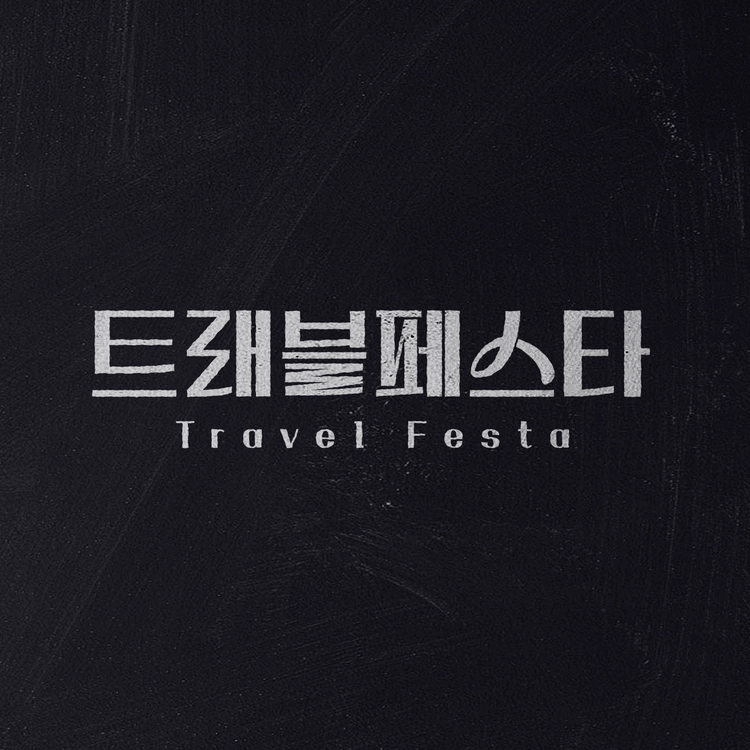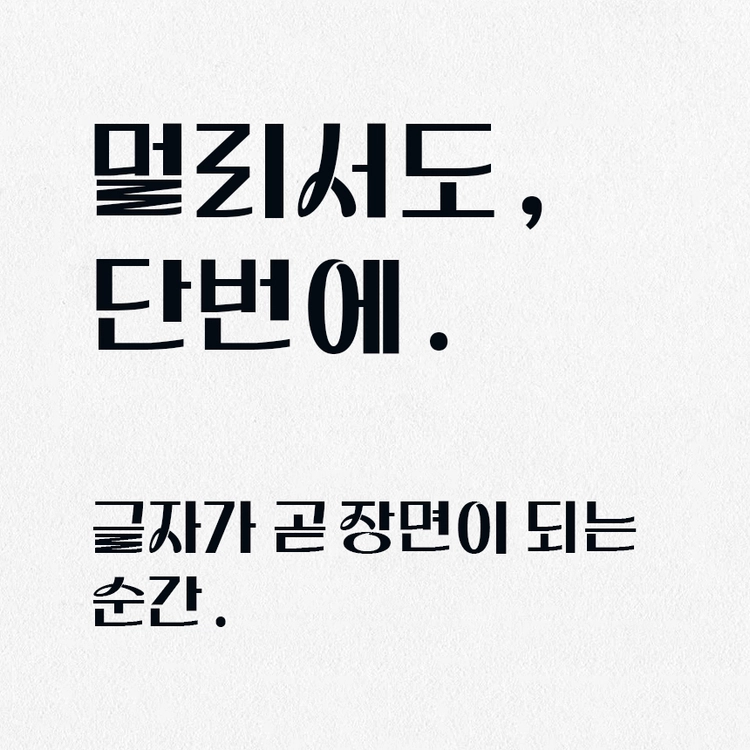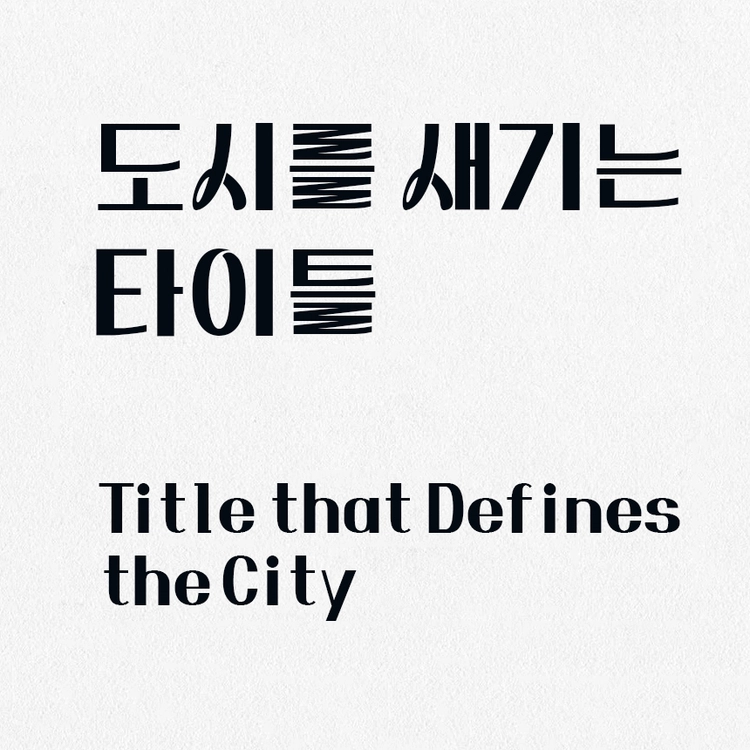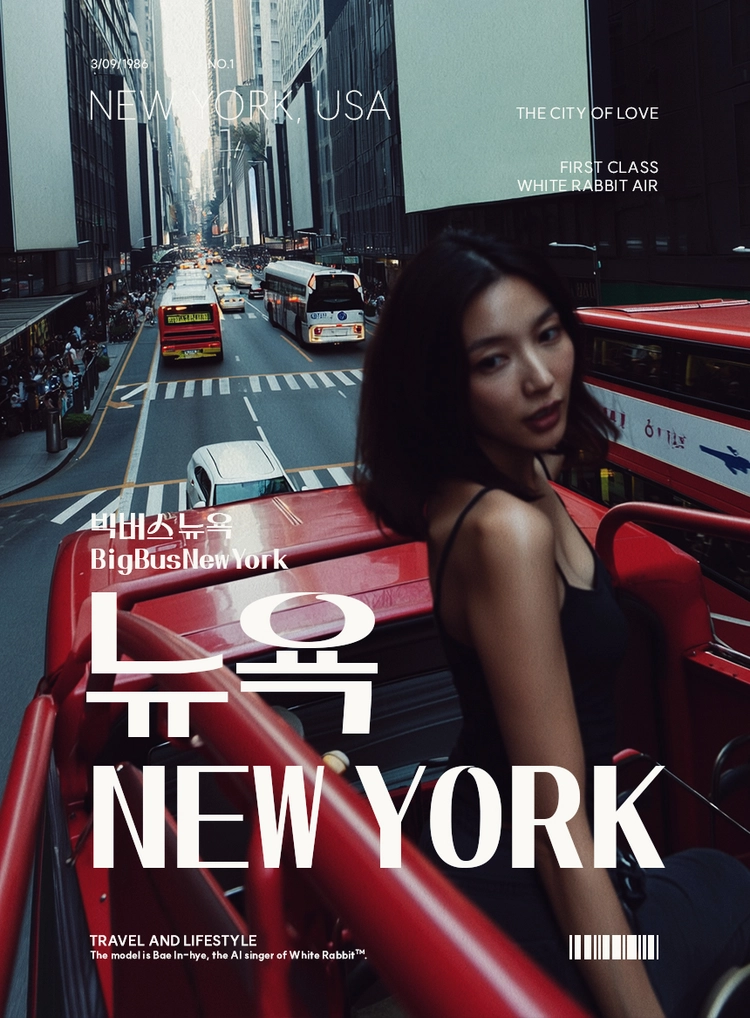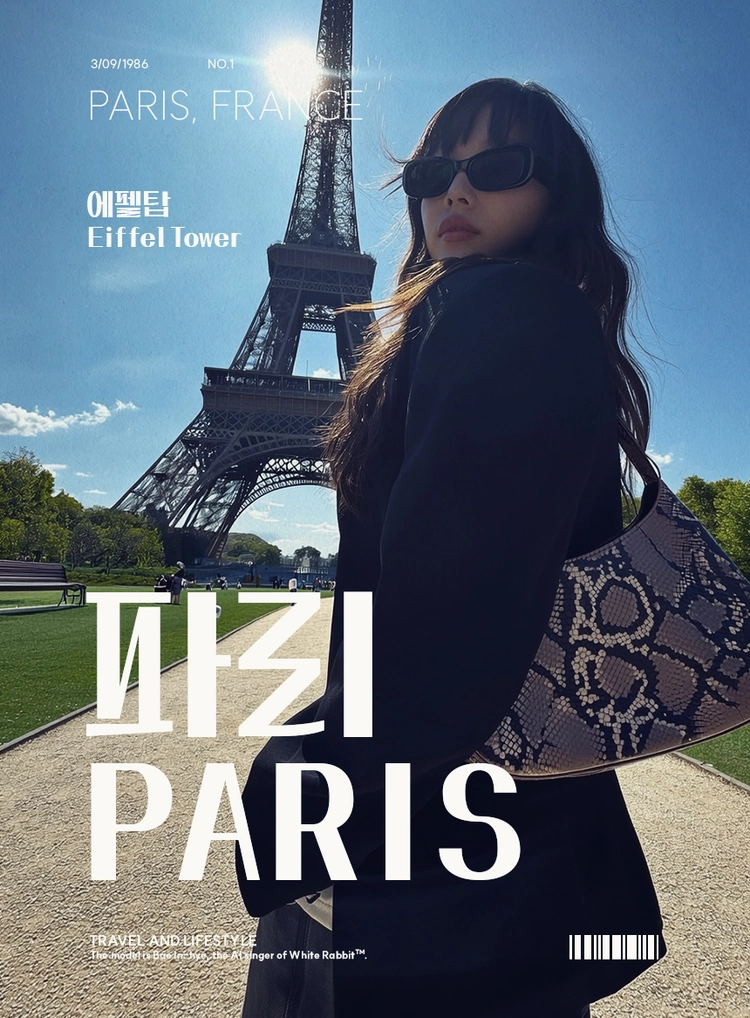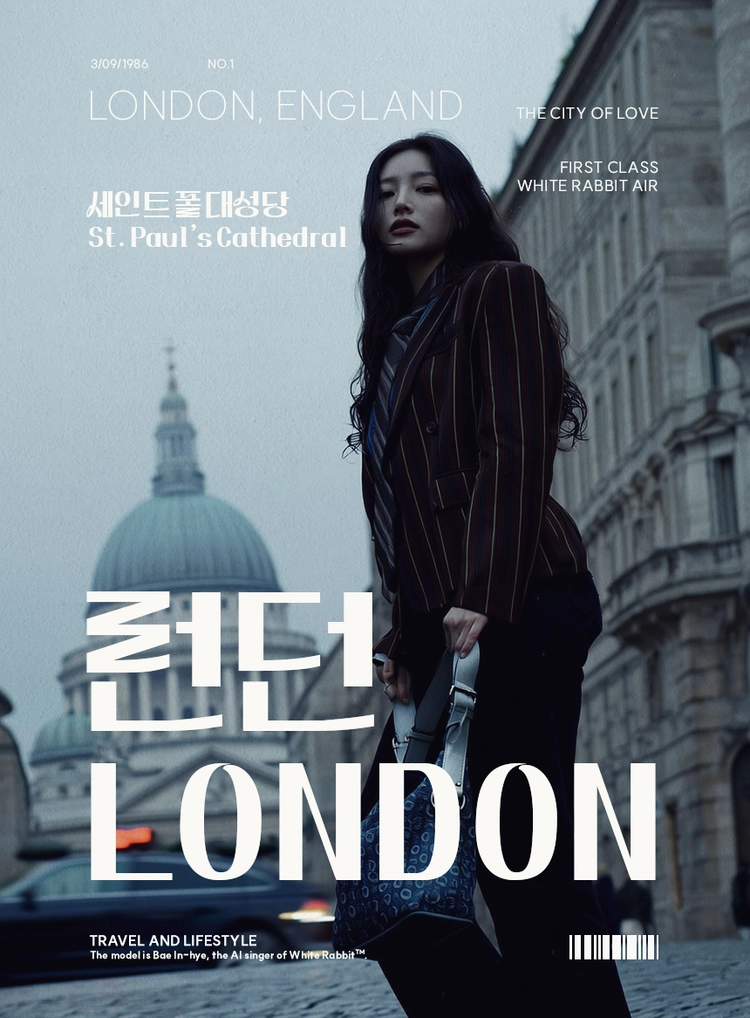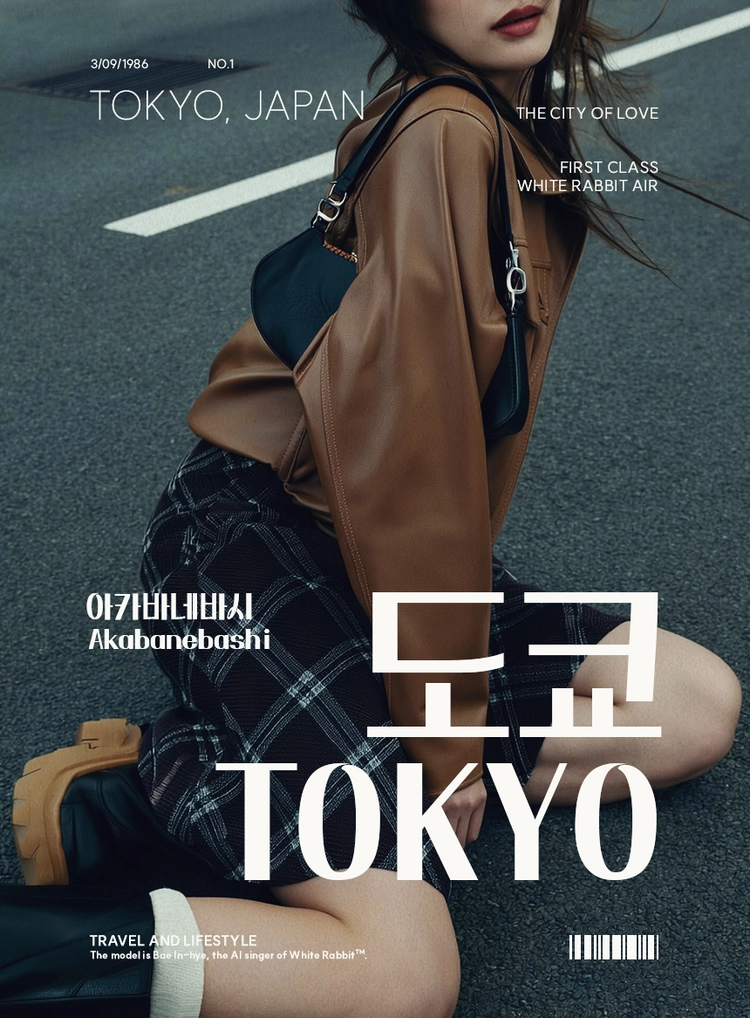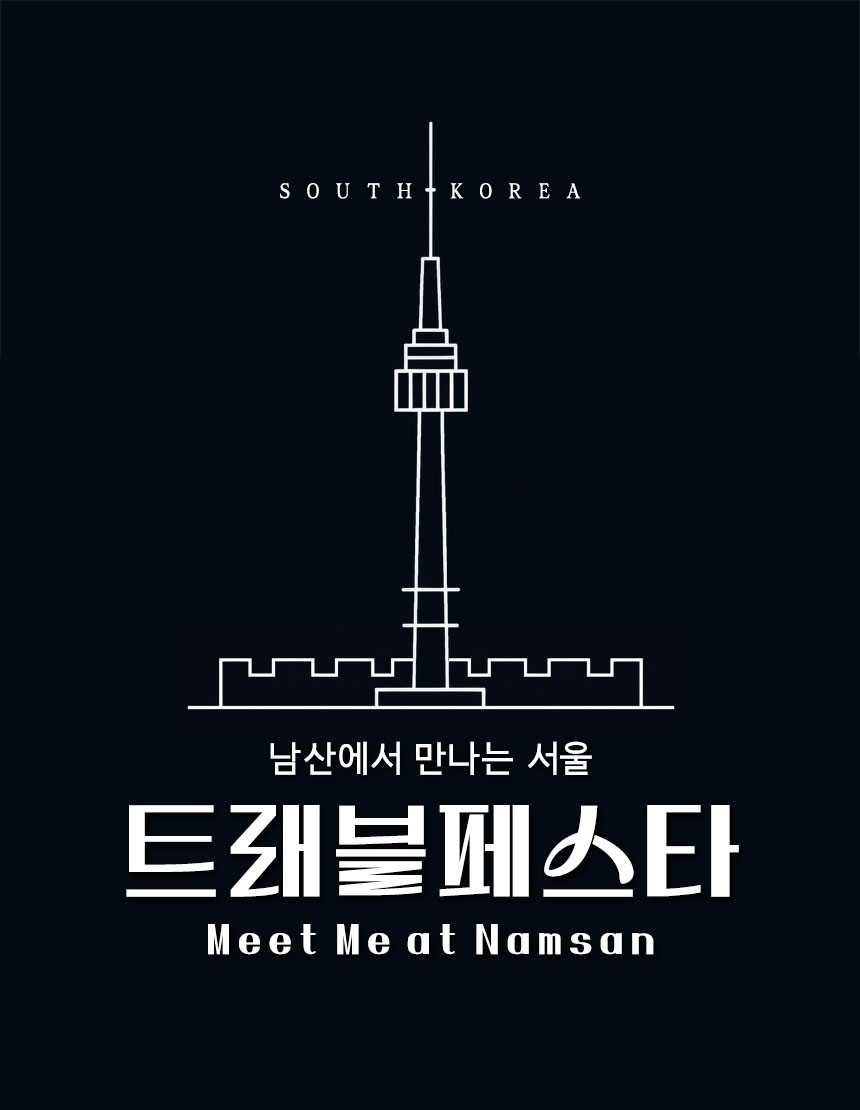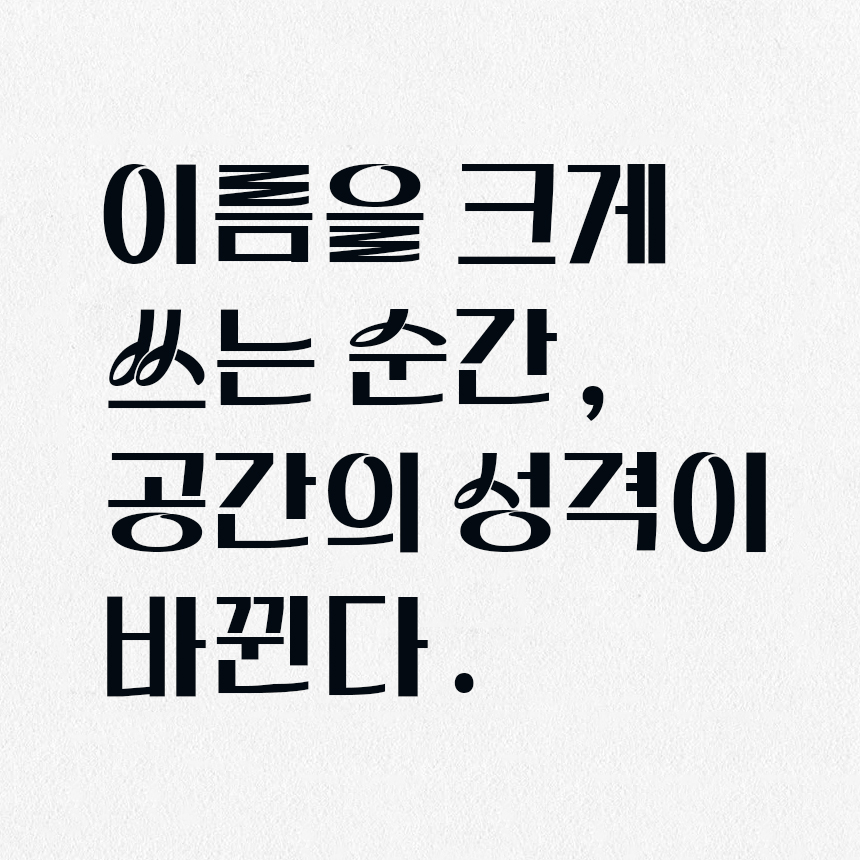
정묵 트래블페스타
여행과 축제의 감성을 담은 정묵 작가의 디스플레이 서체, 트래블페스타
“길 위의 설렘을 담은 글자”정묵 트래블페스타 체는 단단하게 세워진 직선, 과감하게 정리된 획 대비
축제의 현수막처럼 시선을 붙잡고
정묵 트래블페스타는누군가의 여정을 알리는 표지판처럼
대표 글자로 보는 트래블페스타 특징트래블페스타 체는 굵기 대비가 분명한 구조와 절제된 곡선 처리를 통해, 전통적인 명조 감성과 현대적 디스플레이 감각을 동시에 보여주는 서체입니다. 획의 시작과 끝이 명확하게 정리되어 있어 대형 출력물에서도 선명하게 살아나며, 타이틀·헤드라인·포스터·간판용에 최적화된 구조를 갖추고 있습니다. 1. 세로 기둥의 존재감, 자
‘ㅈ’의 상단 구조와 수직 축의 긴장감이 분명합니다. ‘ㅏ’의 직선 중심축이 전체 구조를 단단히 세워 주며, 단문 타이틀에서 또렷하게 살아나는 글자입니다. → 포스터 메인 타이틀 첫 글자로 적합. 2. 확장성과 리듬, 권
‘ㄱ’의 각진 시작과 ‘ㅝ’의 넓은 내부 공간, 받침 ‘ㄴ’의 안정적 마무리가 대비를 만듭니다. 가로 확장이 자연스럽고, 브랜드명·행사명에 사용했을 때 시각적 리듬이 좋습니다. → 3~4글자 행사명에 적합. 3. 구조 밀도의 힘, 동
‘ㄷ’의 단단한 프레임과 ‘ㅇ’의 내부 공간 대비가 선명합니다. 하단 ‘ㅇ’의 안정적 무게 중심이 디스플레이용 폰트의 존재감을 강화합니다. → 현수막·간판용 대형 출력에 적합. 4. 하단 무게감, 평
‘ㅍ’의 구조적 프레임과 ‘ㅇ’의 둥근 대비, 받침 ‘ㅇ’까지 이어지는 하단 밀도가 안정적입니다. 타이틀 하단을 단단히 받쳐주는 글자. → 로고타입 마지막 글자로 적합. 5. 장식성과 임팩트, 꽃
쌍자음 + 쌍받침 구조. 하단 확장이 크고, 장식적 리듬이 강합니다. 트래블페스타처럼 ‘축제·이벤트’ 계열에 특히 어울리는 구조. → 포인트 타이틀·서브 이벤트명에 적합. 트래블페스타 체의 핵심 구조 요약굵기 대비가 명확한 디스플레이 구조, 세로축 중심이 강한 안정형 설계, 받침에서 오는 하단 무게감이 우수하며 대형 출력에서 획 손실이 적음, 타이틀·로고·현수막에 최적화 된 디자인 폰트 이런 분들에게 추천합니다트래블페스타는 ‘눈에 띄는 제목’을 필요로 하는 분들을 위한 글자입니다.